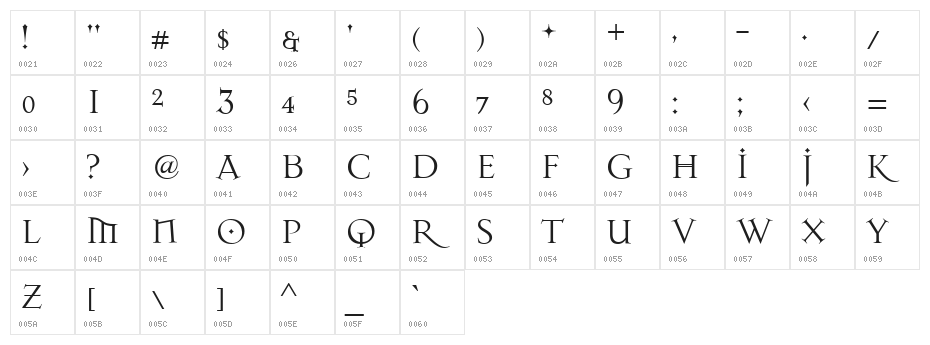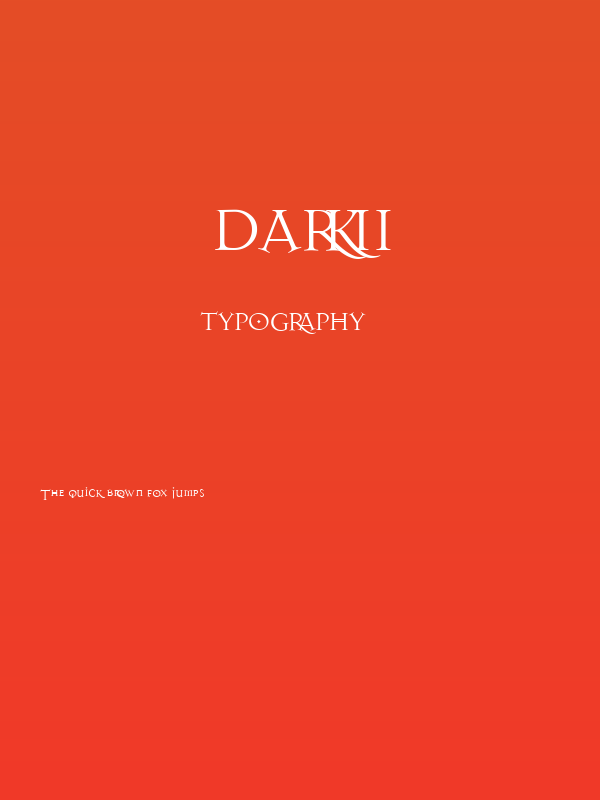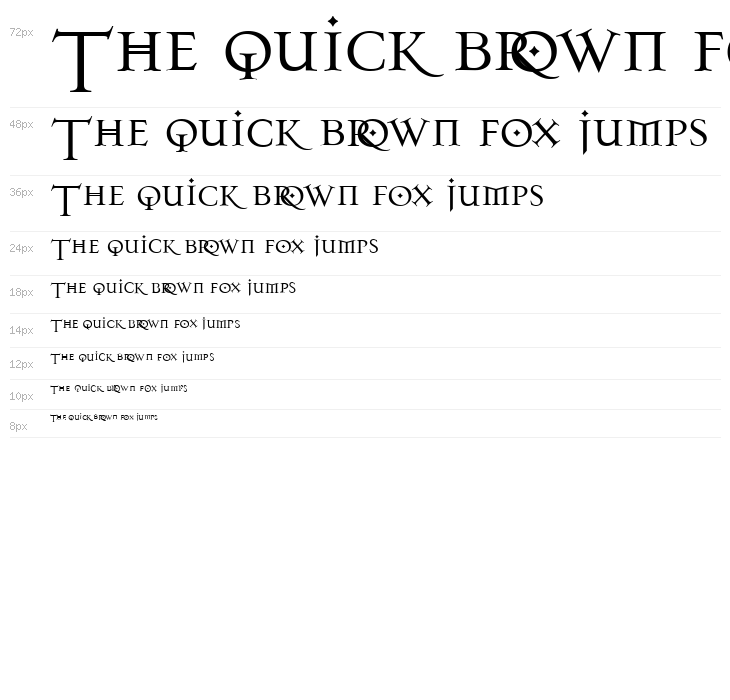
Dark11 Font
| Stil general | Gothic, Decorative |
| Proiecte propuse | Ideal for projects requiring a dramatic and historical feel, such as book covers, posters, or branding for fantasy-themed products. |